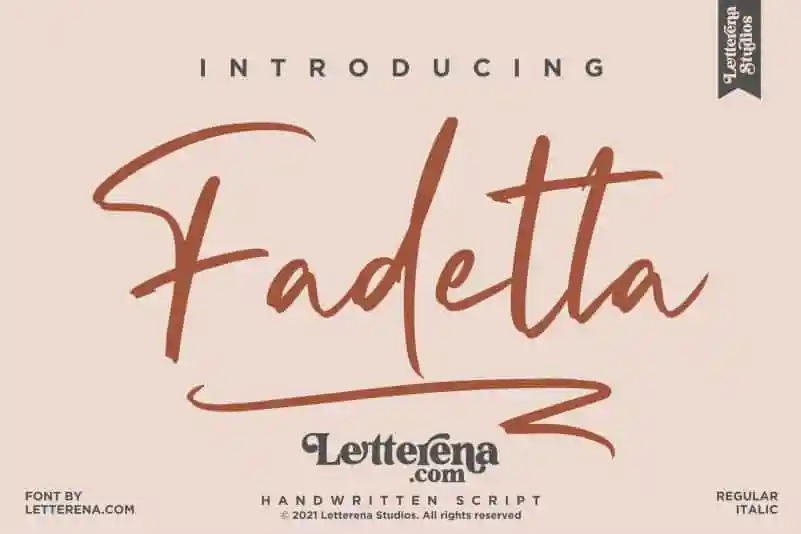
Fadetta Script Font – Download Grátis
A ‘Fadetta Script Font’ é uma elegante linha de escrita cursiva criada pelo designer Letterenastudios. Desenvolvida para projetos que exijam um toque de sofisticação, esta fonte de escrita cursiva romântica é perfeita para inúmeros tipos de trabalho gráfico. Ela se ajusta perfeitamente a criações de logomarcas e projetos de branding, designs de mobiliário e embalagens, talves até até capas de livros, cartões de nome, convites e cartões de agradecimento, etiquetas, fotografias ou desenhos em água e até mesmo para o design de marcações especiais. Seja qual for seu projeto, esta fonte traz um sabor único à sua criação. Não perca tempo com uma impressão fraca, escolha a ‘Fadetta Script Font’ para dar vida ao seu trabalho gráfico!